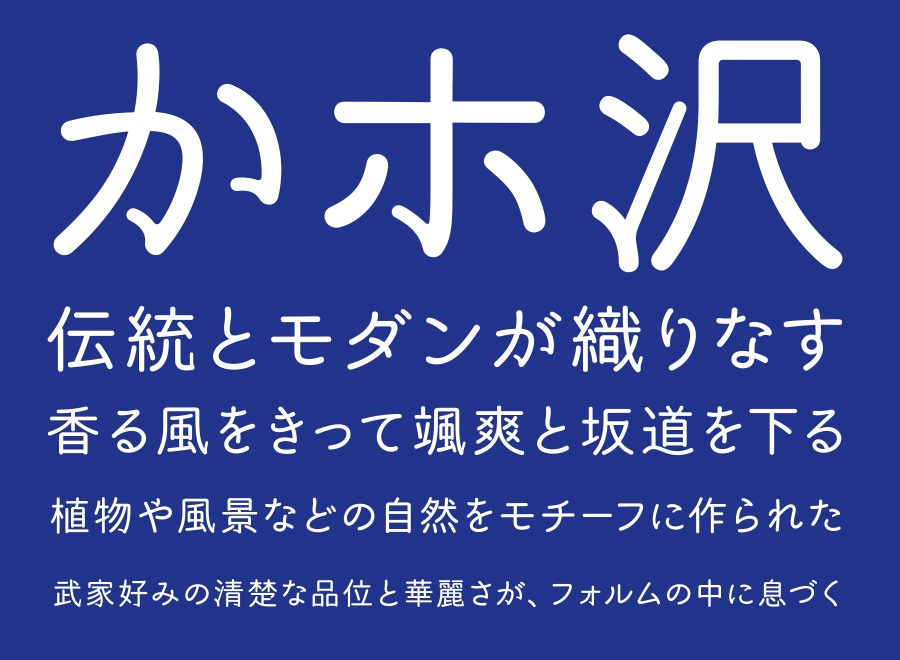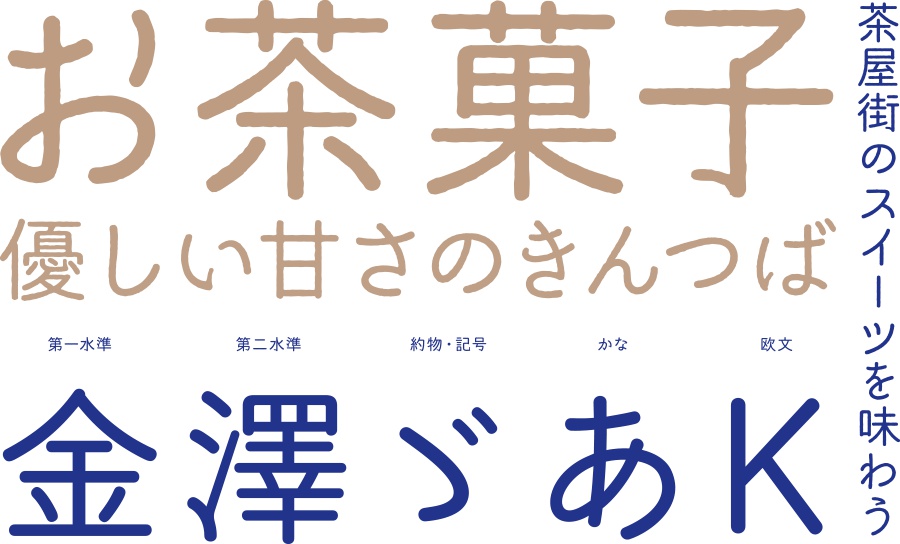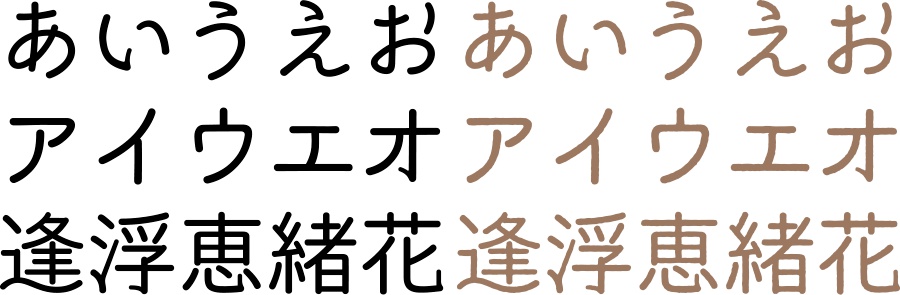
かなざわ本丸ゴシック - 2フォントSET
金沢城のある、金沢市をイメージした華麗な丸ゴシック体です。武家好みの気品ある形の中に、躍動感のある華麗な美しさを含んでいます。クラシックな柔らかさの中にキレのある表現が可能です。伝統的な和風からモダンな雰囲気まで幅広くお使い頂けます。 特典として線がガタガタとして手書きのような味わいのある文字の、かなざわ本丸ゴシック茶菓子が付いてきます。 収録フォント(2書体) かなざわ本丸ゴシック(レギュラー)、かなざわ本丸ゴシック茶菓子(ラフ) 動作環境 Mac:システム/OS X対応(10.x)〜最新のOS X Windows:OS/日本語版Windows2000、XP、VISTA、Windows7〜11以降 フォント形式:OpenTypeフォント、TrueTypeフォント 収録文字数について 収録文字数4,072文字(第一水準2965文字+第二水準460文字+ひらがな.カタカナ.約物.記号.アルファベット等647文字) 安心して使えるロイヤリティフリーの書体 あらゆる商用・デザイン用途(印刷物・ゲーム・アプリ・映像・動画・ロゴ・同人作品)に使用できる、商用申請の必要のないロイヤリティフリーの書体になります。文字の加工・変形も可能です。ご安心ください。